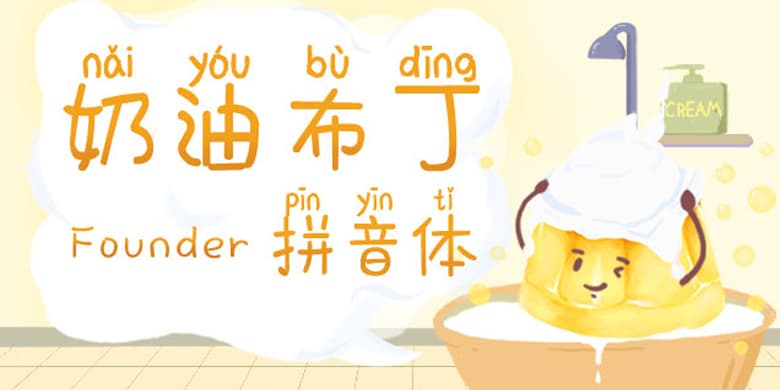
品牌:方正手迹设计师:俞亦婷发行时间:2020字库编码:大陆简体(GB2312-80)分类:创意书写字体属性:精品字
这是一款趣味十足的拼音字体,笔画圆润,转角较大,结构变化多样,高低胖瘦保持一致。即使加上了拼音,阅读起来也丝毫没有障碍。适用于少年儿童类的书刊、品牌广告和产品包装设计,以及社交网络的个性化用字。